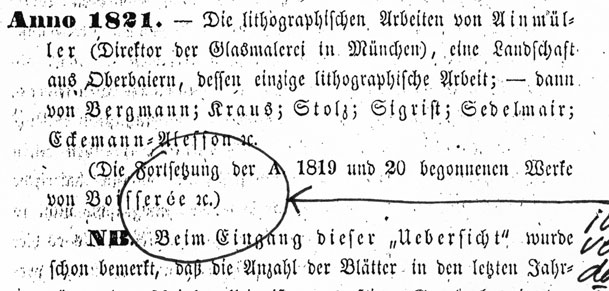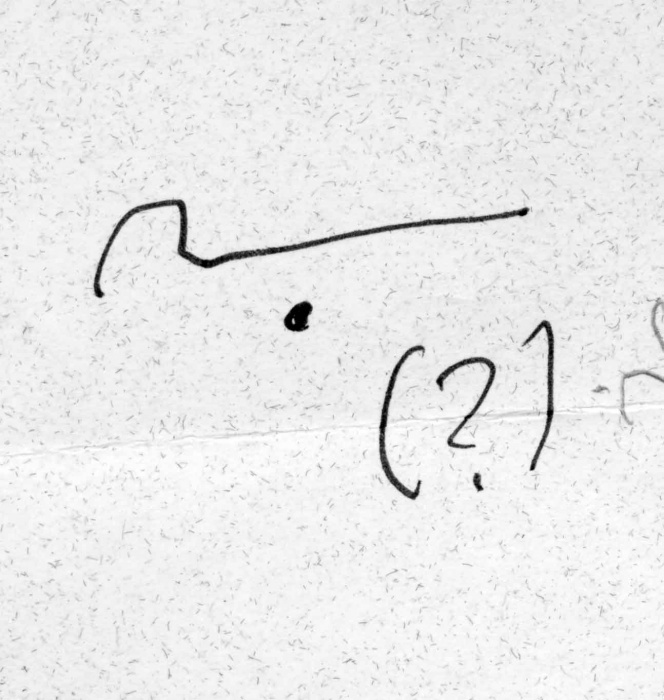
Wofür stehen diese Zeichen?
Ich bin auf der Suche nach der Erklärung für folgende Zeichen aus einem handschriftlichen deutschsprachigen Manuskript aus dem 19. Jahrhundert und würde mich sehr freuen, wenn mir hier jemand weiterhelfen könnte.
1. Handelt es sich um ein auf dem eigenen Punkt liegendes Fragezeichen. So sieht es für mich zumindest aus. Es könnte möglicherweise für eine Art Anführung oder Hervorhebung stehen ... (Bild 1)
2. Das zweite ist ebenfalls ein mir unerklärliches und aus dem textlichen Zusammenhang nicht eindeutig erklärbares Zeichen. Auf dem einen Bild ist die handschriftlicheFassung , auf dem zweiten Bild von einer schlechten Kopie eine bleigesetzte Fassung möglicherweise des selben Zeichens. Sicher bin ich mir dessen allerdings nicht. Ich hab dieses Zeichen auch noch nie in irgendeinem Setzkasten oder Setzkastenschema gesehen und weiß auch nicht, wie man danach forschen könnte, wenn ma nicht weiß, wie es heißt.
Ich würde nun gern wissen, was diese Zeichen bedeuten und wie sie heißen. Und ich würde gern wissen, ob es diese Zeichen auch in irgendeinem Font gibt, weil ich sie ja irgendwie setzen muss ...
Um auf das 2. zu antworten, es ist nicht dasselbe Zeichen. Das erste ist ein X, das andere ist ein rundes r, welches eigentlich nur in rc für usw. benutzt wird.
das andere ist ein rundes r, welches eigentlich nur in rc für usw. benutzt wird.
Streng genommen ist es wohl kein rundes r (), sondern ein tironisches Et, das aber optisch starke Ähnlichkeit zum runden r aufwies, bzw. von diesem nicht zu unterscheiden war, sofern denn beide in derselben Schrift auftauchten. Hier steht es auf jeden fall für et, ꝛc. ist also etc.
PS: Das findest Du übrigens unter anderem in der Unifraktur Maguntia.
PPS: Beim verbleibenden Zeichen könnte der Kontext helfen.
Im übrigen war diese Zusammenstellung aus trionischem Et und dem c sowie sem Abkürzungspunkt für "et cetera" derart verbreitet, dass diese Kombination als eine Ligatur-ähnliche Glyphe so im Setzkasten zu finden war, wenn auch in dem, mit den Sonderzeichen, wo sich auch andere, damals oft gebrauchte Zeichen, wie das Pfund-Zeichen, das Pfennig-Zeichen (auch als Deleatur-Zeichen verwendet) ₰ und das handschriftliche M für Mark befand
Das mit dem runden R wußte ich nicht, finde es aber sehr interessant. Vor allem die Ligatur aus dem Sondersetzkasten würde mich interessieren ...
Gabs die vielleicht sogar für Antiqua? Und: gibts die irgendwo "für Computer"? Und: gabs soetwas auch in "Schreibschrift" - vielleicht ist mein "X" die Schreibschriftvariante davon? War so ein bißchen meine Hoffnung ...
Bei den eigentlich wichtigen Zeichen aus dem Manuskript sind wir ja noch nicht wirklich erkenntnisreicher. Zum "liegenden Fragezeichen" gibt es nicht mal ne These, bei dem anderen Zeichen meine ich aber, dass es ein X nicht ist. Es sei denn, ein einzelnes X hätte eine Bedeutung - im Sinne von etc., u.v.m., u.a. oder so etwas in der Richtung. Eine Lektorin meinte, dass könne auch als "Chi" verstanden werden, ohne eine schlüssige Theorie zu haben, wofür das nun wiederum stünde ...
Es bleibt also weiter ein Rätsel. Das Blöde ist: ich hab bisher keine Bilder von der Originalhandschrift (und weiß auch nicht, ob ich welche bekomme, auf denen diese Zeichen drauf sind, das gesamte Manuskript hat 360 Seiten und ich bekomme wahrscheinlich nur 2 bis 3 Beispielseitenbilder), sondern nur die oben gezeigten abgemalten Skizzen und das Manuskript als Worddatei, in dem diese Zeichen als XXX und ??? geschrieben sind ...
Ich such mal ein paar Text-Stellen raus und stell sie dann hier rein, vielleicht bringt das ja die Erleuchtung.
Vor allem die Ligatur aus dem Sondersetzkasten würde mich interessieren ...
Wenn ich das richtig verstanden habe, handelt es sich nur um eine Ligatur-ähnliche Glyphe ꝛc, was in der Endzeit des runden r ja auch nahe lag, da es nur noch in der Kombination ꝛc. auftauchte, man sich also die Arbeit spare konnte, ein c herauszufischen (gab es sowas dann auch für Qu?).
Gabs die vielleicht sogar für Antiqua?
Das halte ich für äußerst unwahrscheinlich. Das runde r in Antiqua existiert ja bereits einzig und allein seitdem es nach seiner Aufnahme in den Unicode der Vollständigkeit halber in einige Schriften aufgenommen wurde.
gab es sowas dann auch für Qu?
Ja, in einigen (wenigen) Schriften wurde eine Qu-Ligatur gegossen - z.B. bei einigen Schreibschriften (Splendor und/oder Arabella beispielsweise - die bringe ich immer durcheinander) und ich glaube auch in einigen Antiquas mit besonders viel Schwung im Q-Abstrich ... ich schau gelegentlich mal nach, wo ich sowas finde ...
Als ich heute über dieses Bild gestolpert bin, weckte dies Erinnerungen an diesen Thread. Zwar sah das letzte Zeichen letzten Endes doch deutlich anders aus, aber vielleicht hilft’s.
PS: Das hier ist schon näher dran.